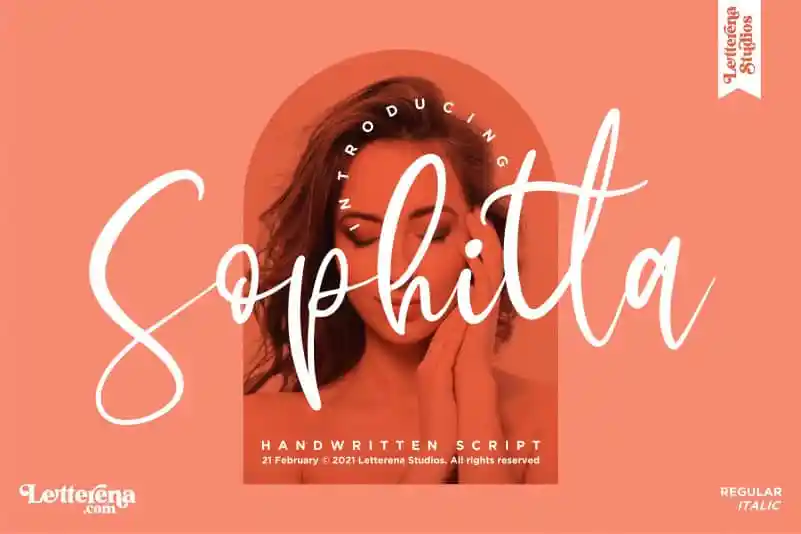
A Sophitta Script Font é uma fonte de escrita à mão que traz a romantização do estilo do xarope. Com sua elegância única, essa fonte foi projetada para abranger um vasto espectro de projetos, desde o design de logotipos e identidades visuais até as etiquetas e os selinhos em produtos. Suas linhas fluidas e sua tipografia delicada fazem dela uma escolha ideal tanto para trabalhos comuns quanto para aquelas iniciativas que exigem um toque de luxo, como capas de livros, cartões de nome, convites, aniversários ou até mesmo pacotes de chá. Perfeita para aqueles que desejam trazer um sabor autêntico e sofisticado aos seus projetos. Seja você uma designer gráfica procura a perfeição em seu trabalho, ou simplesmente alguém que busca expressar sua personalidade com uma fonte única e elegante – a Sophitta Script Font é a escolha certa para seu próximo projeto. A Sophie é da letra nasta studios, um designer de letras famoso por suas criações únicas e sofisticadas. Com essa fonte, você pode se juntar à outros criadores que já escolheram a Sophie como o centro do design de seus projetos. Seja uma marca em seu novo produto ou um design de arte para uma publicação especial, a Sophitta Script Font estará lá, pronta para ajudá-lo a capturar sua inspiração e transformá-la em algo realmente único.